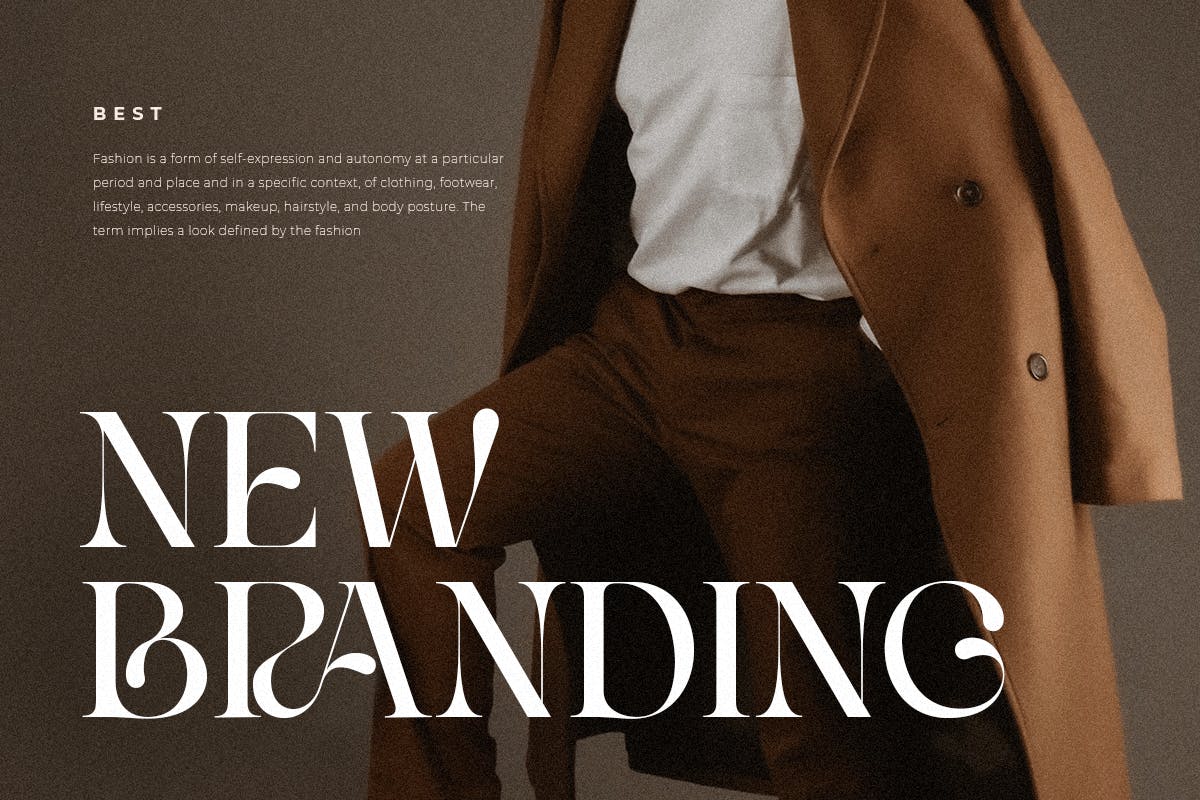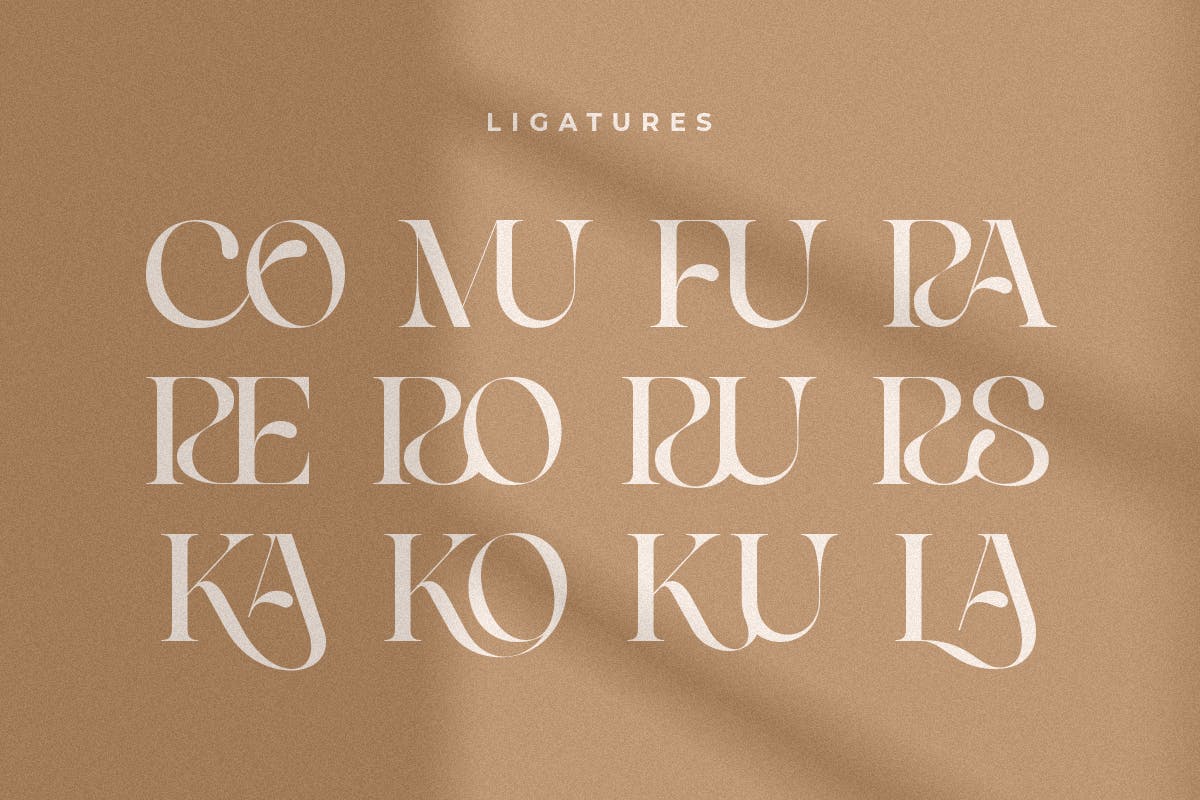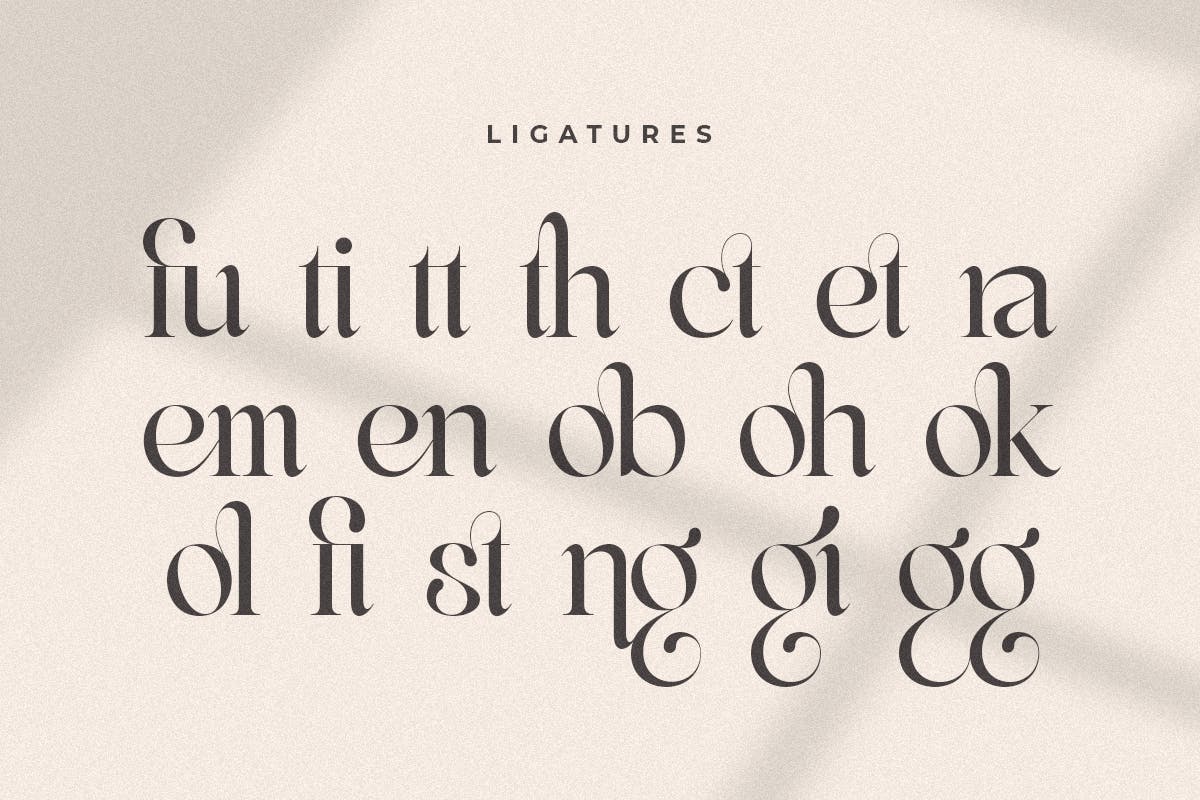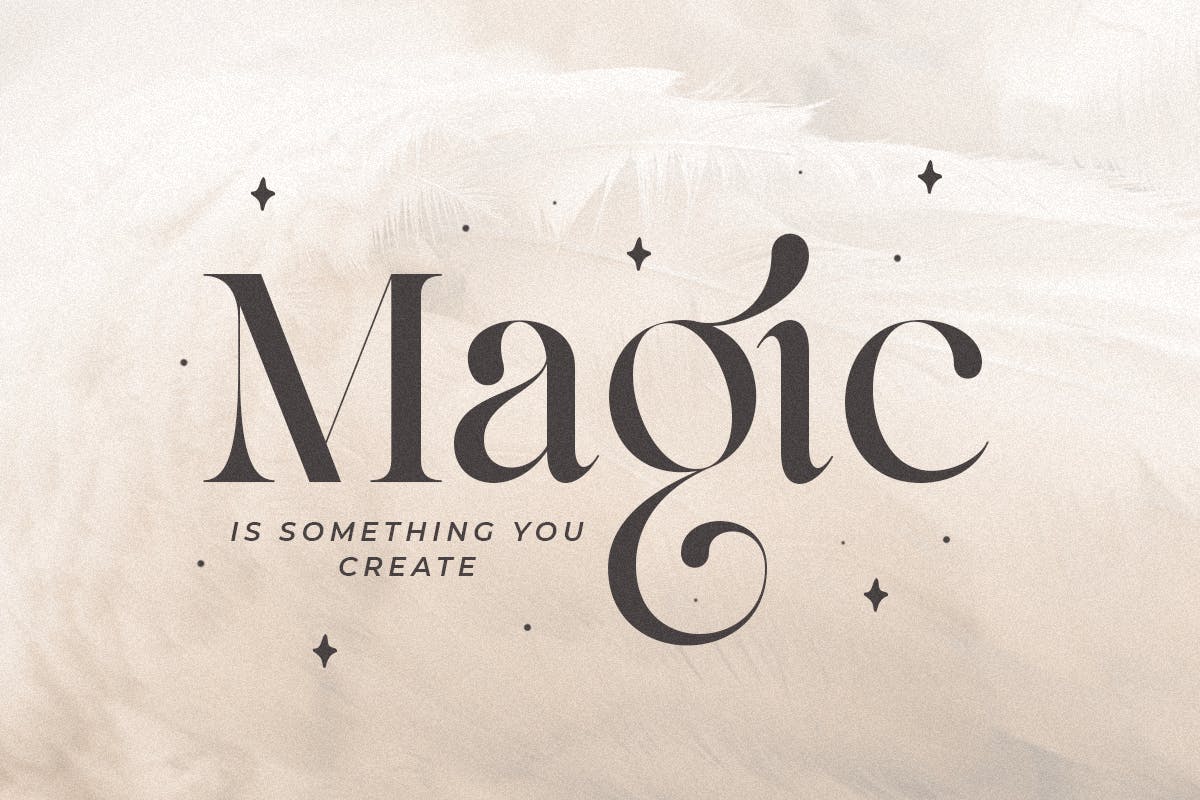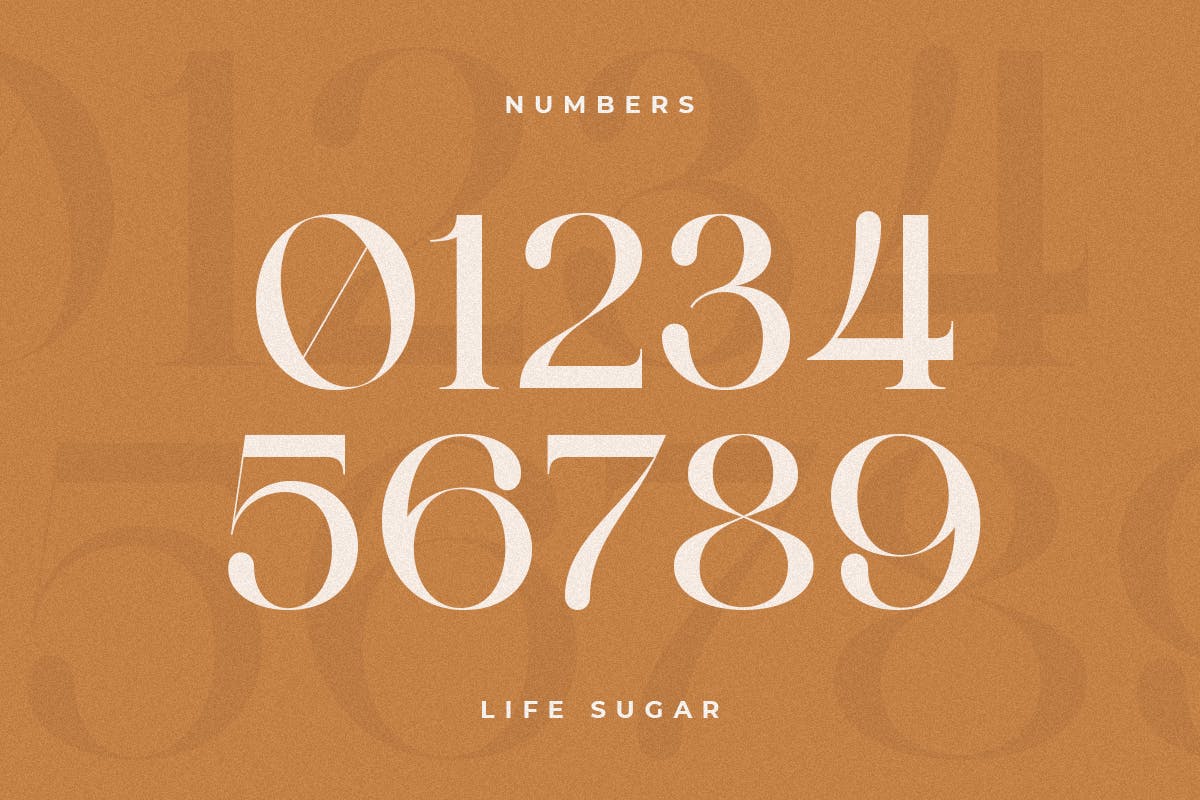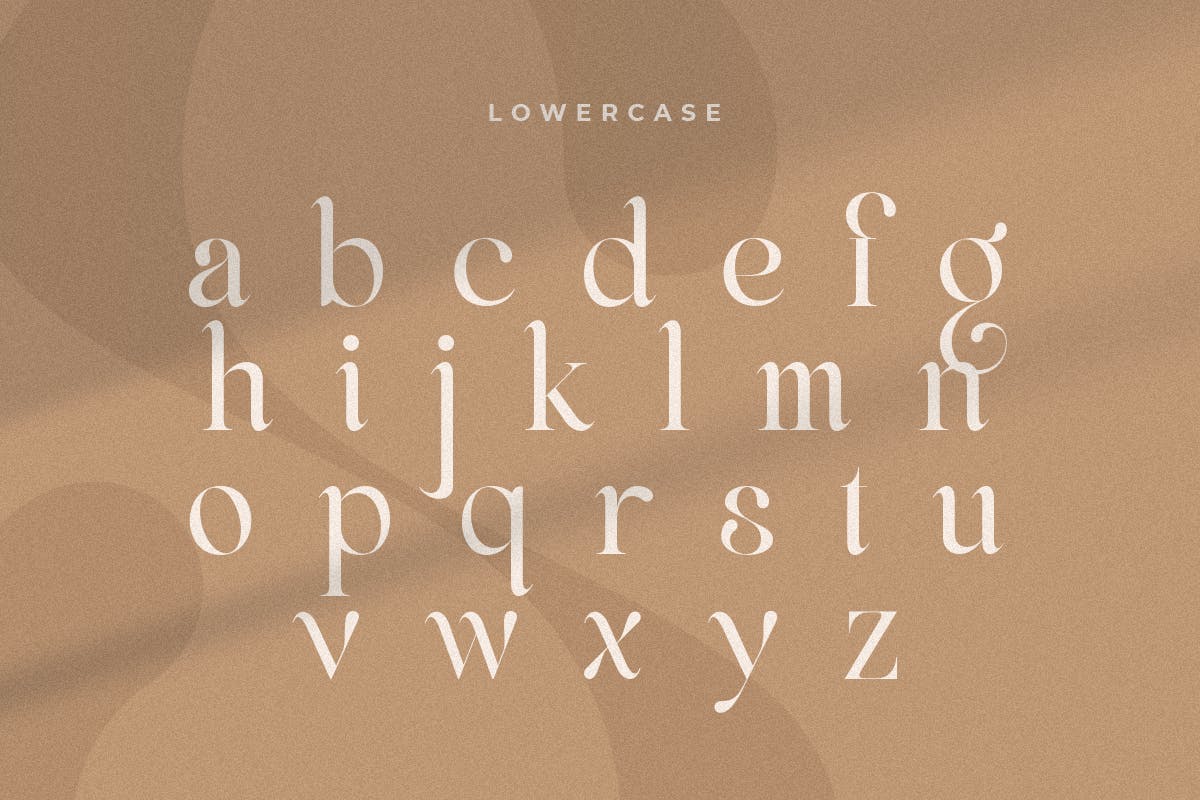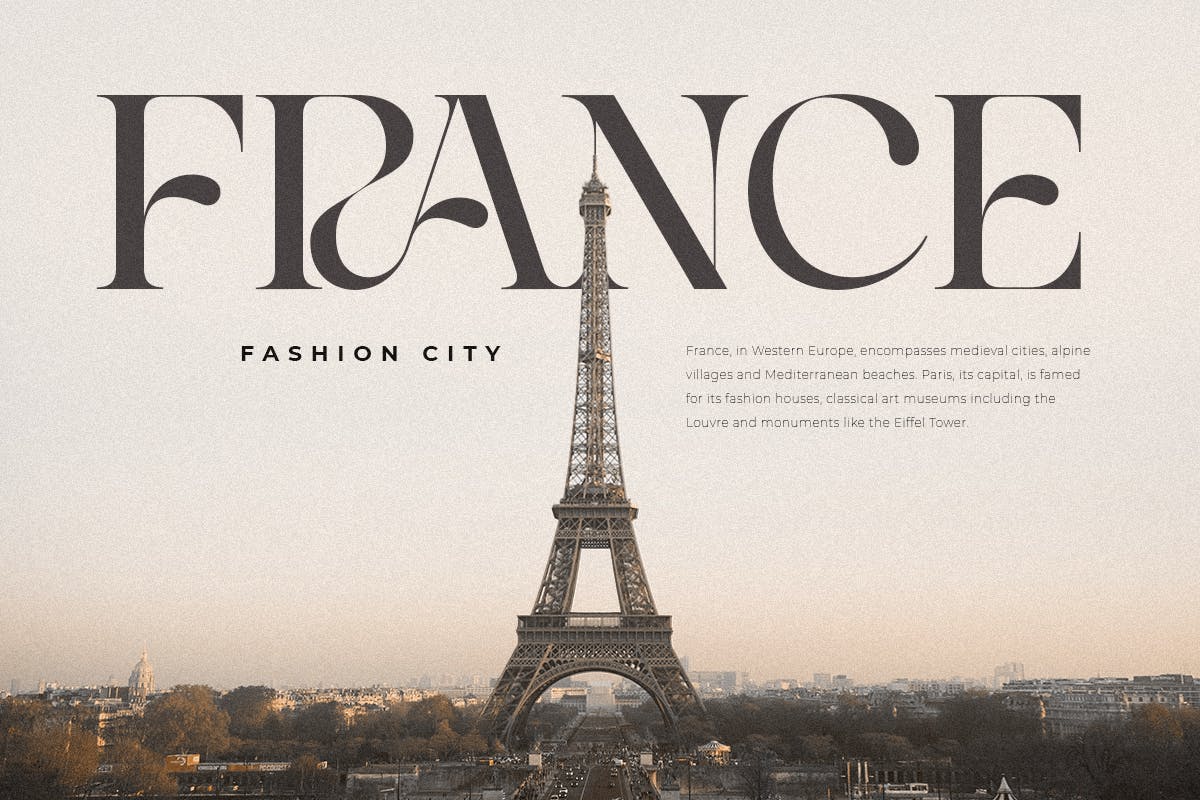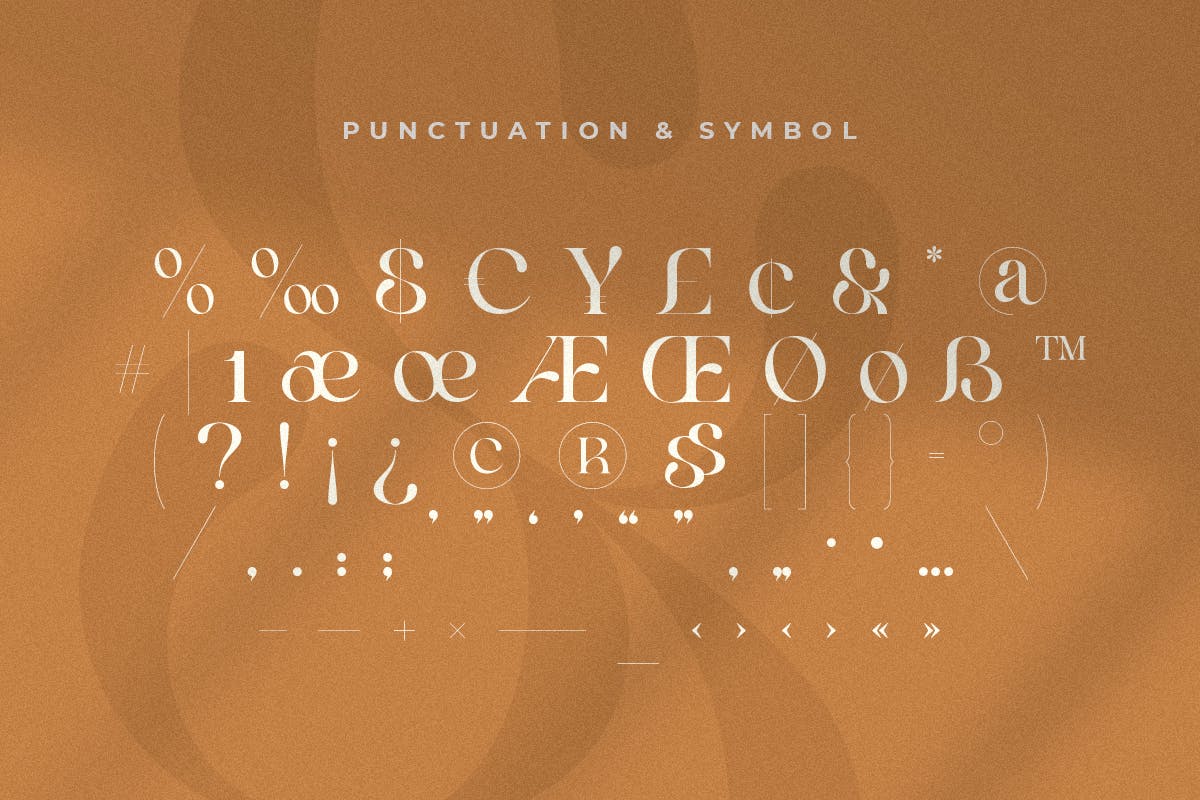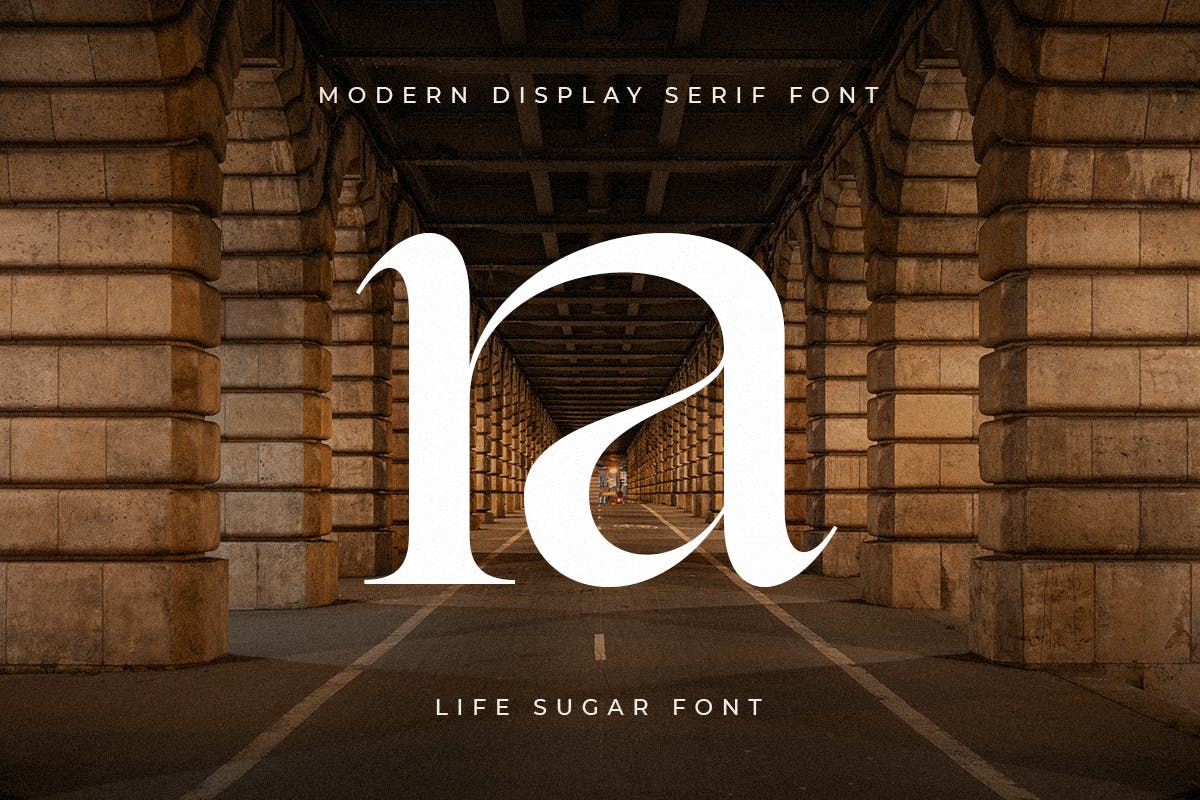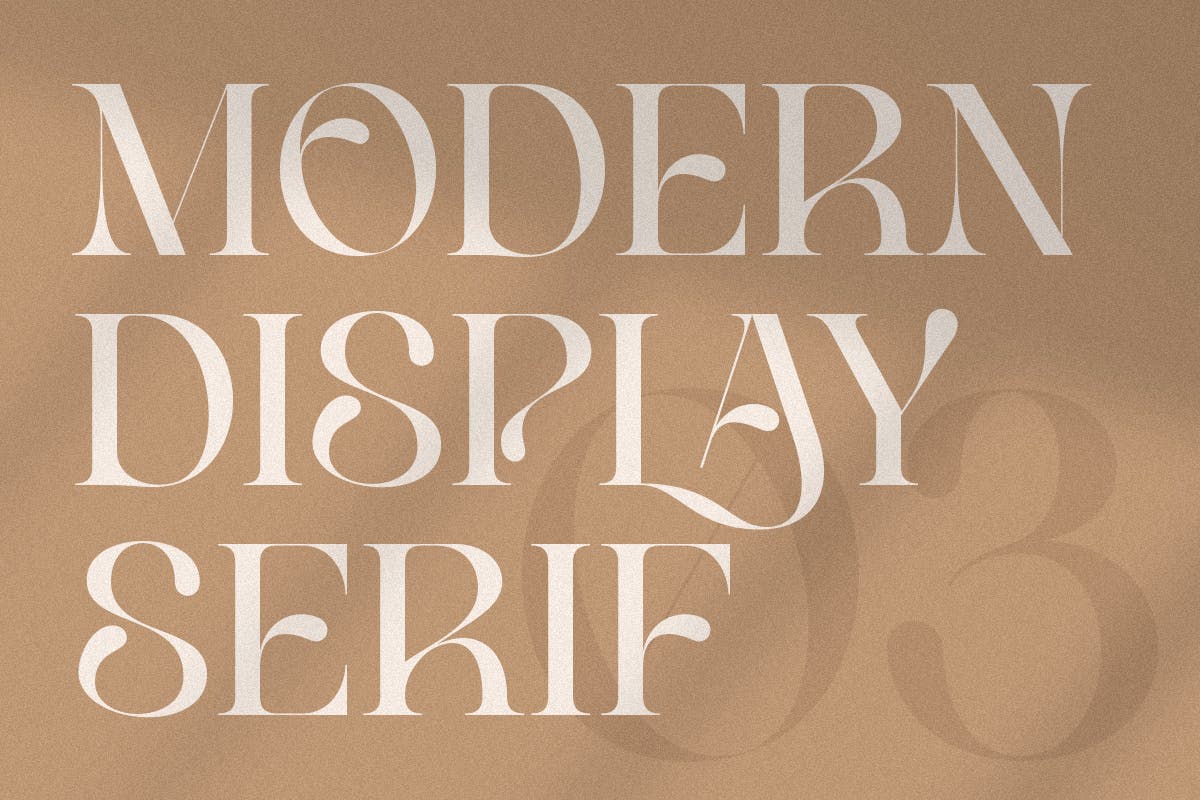
فونت Life Sugar یک فونت مدرن و لاکچری با طراحی منحصر به فرد است که به خوبی تعادل را بین زیبایی و خوانایی برقرار میکند. این فونت سریفی با ظاهری مجلل و چندمنظوره است که به راحتی میتوانید با انتخاب گزینههای مختلف، اشکال و تنوعات منحصر به فردی را در عرض چند ثانیه ایجاد کنید. این فونت برای پروژههای برندینگ، طراحی لوگو، طراحی عروسی، پستهای شبکههای اجتماعی، تبلیغات، بستهبندی محصولات، طراحی محصولات، برچسب، عکاسی، واترمارک، دعوتنامه، لوازمالتحریر و هر پروژهای که نیاز به خوانایی بالا دارد، مناسب است.